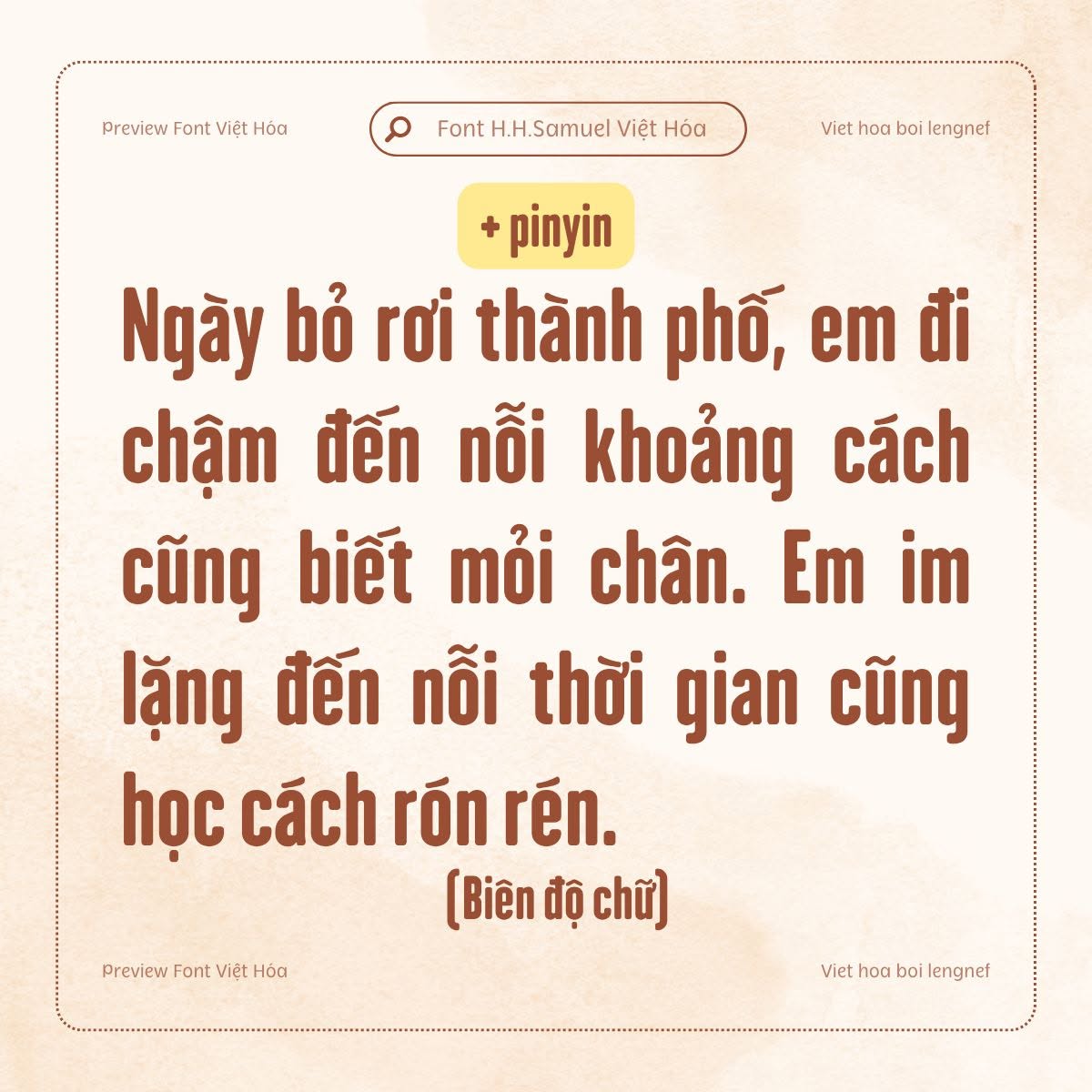
Font LF H.H. Samuel
H.H. Samuel là một kiểu chữ sans-serif hình học, với các góc bo tròn làm sáng các khoảng trống bên trong chữ, vì độ nén của nó làm giảm khả năng đọc ở kích thước nhỏ. Được lấy cảm hứng từ các kiểu chữ nhân văn grotesque của đầu và giữa thế kỷ 20 mà vẫn giữ phong cách Art Deco.
H.H. Samuel có khả năng đọc tối ưu ở kích thước lớn, nên sử dụng ở kích thước trên 34pt. Phù hợp thiết kế bất kỳ tài liệu quảng cáo nào như: áp phích, tờ rơi, biển hiệu, chữ viết tay, v.v…